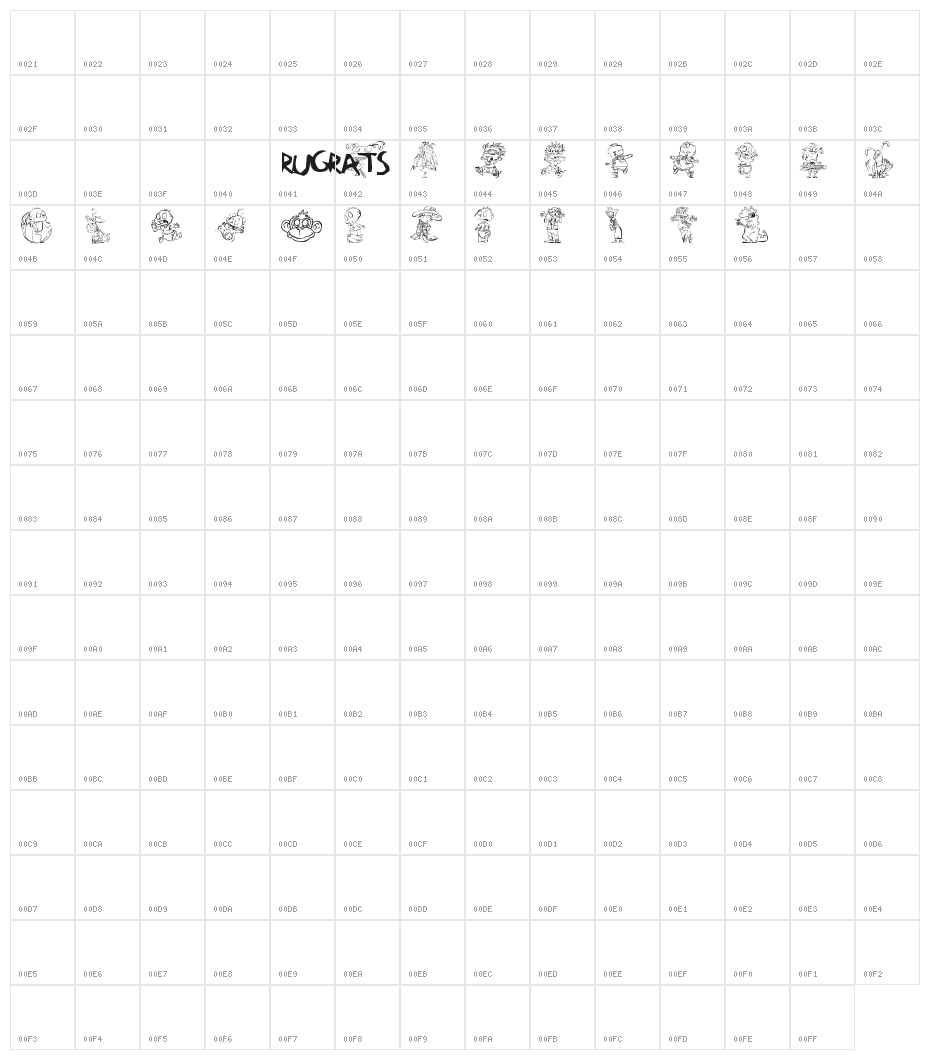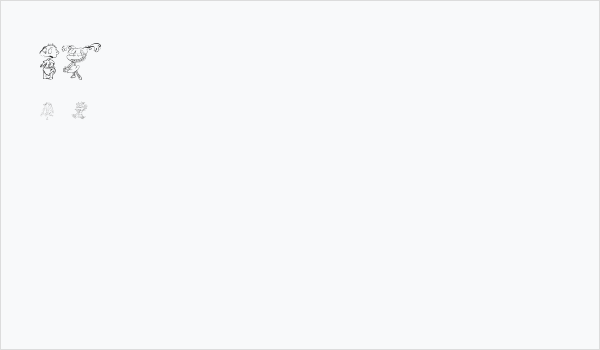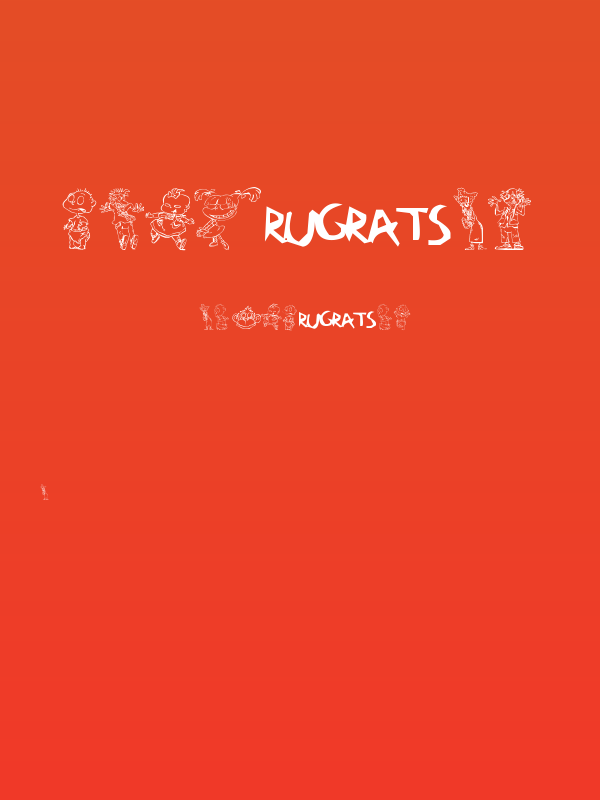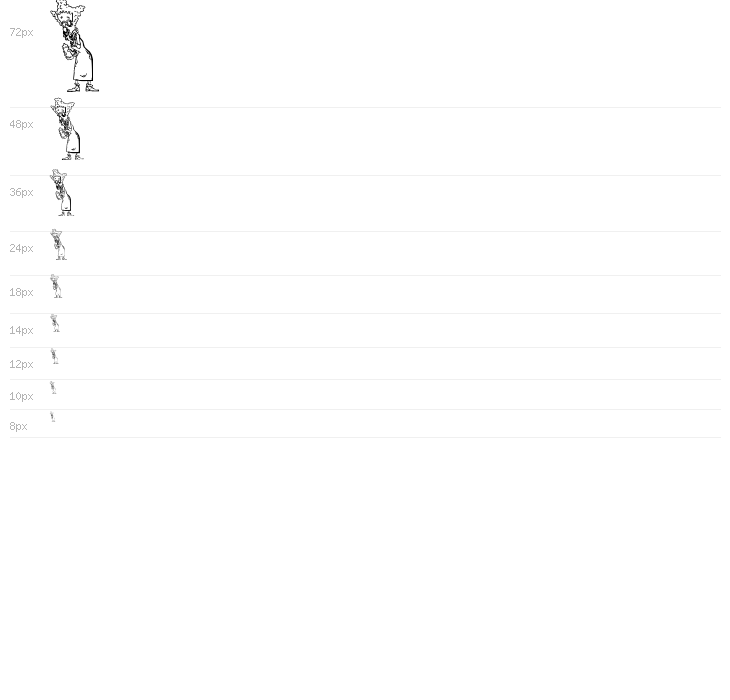
RugBats Font
✎ Dingbats
| Gesamtstil | Playful, Whimsical |
| Anwendungsfall | Logos, Illustrations |
| Vorgeschlagene Projekte | This style is suitable for animated series branding, children's book illustrations, or merchandise design. |